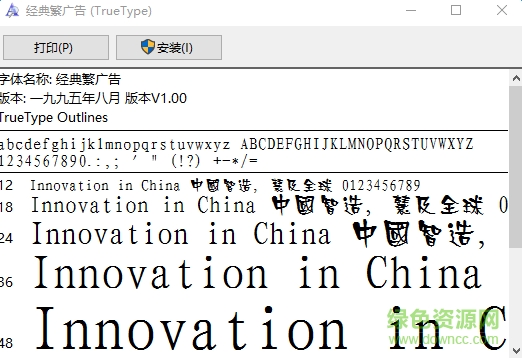
經(jīng)典繁廣告字體是經(jīng)典字庫(kù)中很有特點(diǎn)的一款電腦字體,該字體寫(xiě)出來(lái)的字是很好看的,可以用于很多方面,書(shū)本印刷、廣告設(shè)計(jì)等都是可以的,歡迎大家來(lái)綠色資源網(wǎng)下載。
經(jīng)典繁廣告字體是一款很不錯(cuò)的電腦字體,不僅字形美觀,實(shí)用性也很強(qiáng),喜歡這款字體的朋友可以來(lái)綠色資源網(wǎng)下載。